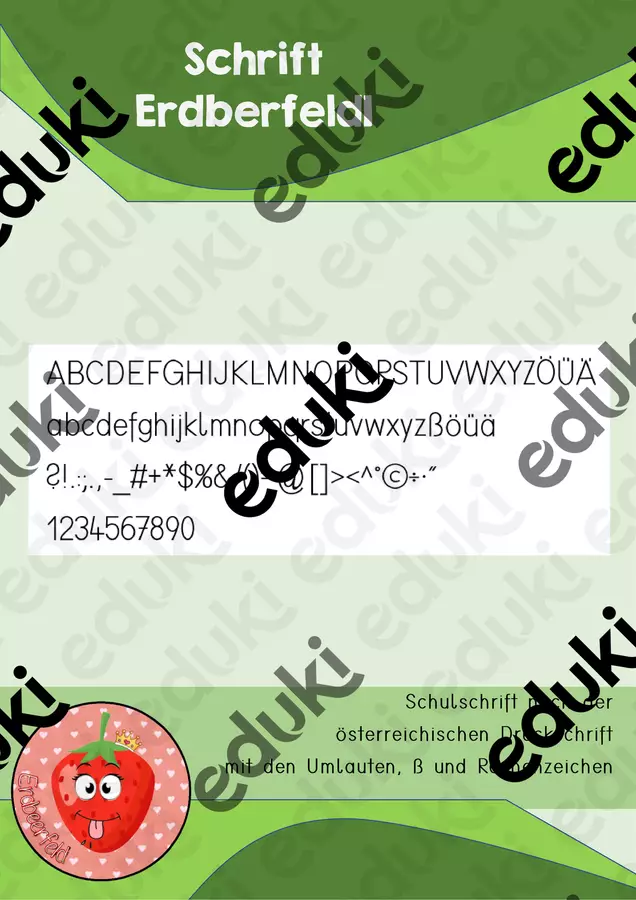
Ich weiß ja nicht wie es euch so mit den Schriftarten geht, aber für mich war es immer furchtbar die Zeit die ich zur Materialerstellung hatte vorwiegend in die Suche nach einer passenden Schrift zu stecken.
Deshalb habe ich mir diese Zeit genommen um eine eigene Schrift zu erstellen, eben ganz genau auf meine Bedürfnisse angepasst. Ich hoffe, dass ich damit jemandem etwas Zeit sparen kann.
Ich habe besonders darauf geachtet, dass das f unter die Zeile geht, das l endlich mal sein Häkchen hat, das ß und die Umlaute ö ü ä auch mitspielen dürfen usw.
Angepasst ist die Schrift auf die österreichische Druckschrift.
Schriftart Erdberfeld1